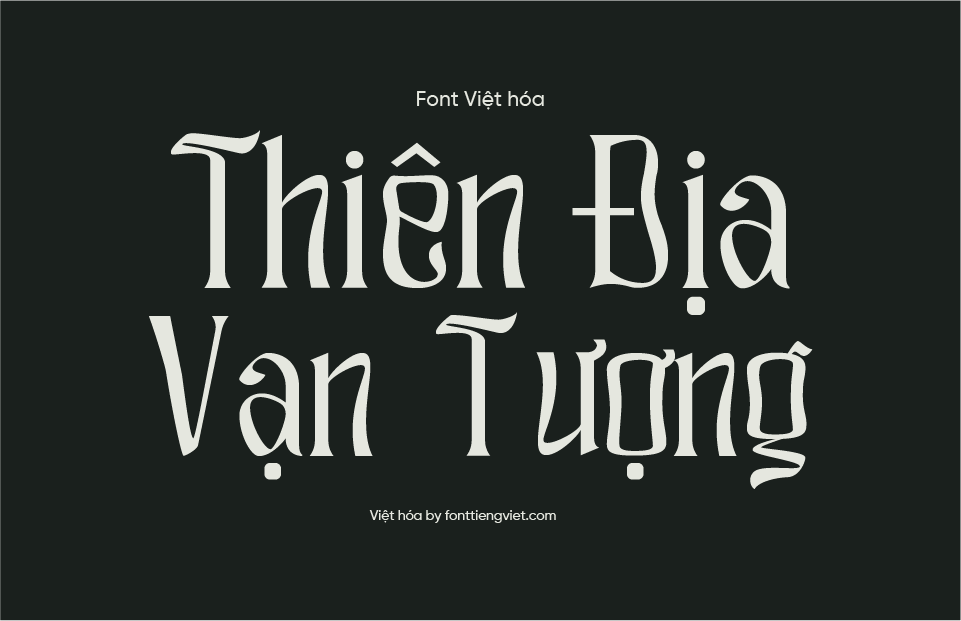
Font Việt hóa 1FTV Raghlick
Trong thế giới đồ họa hiện đại, việc lựa chọn một Font Miễn Phí chất lượng là yếu tố then chốt giúp tác phẩm trở nên ấn tượng. Font Việt hóa 1FTV Raghlick nổi lên như một lựa chọn hoàn hảo cho những ai đang tìm kiếm sự kết hợp giữa nét cổ điển và hơi thở hiện đại. Với bộ ký tự được chăm chút tỉ mỉ, phông chữ này giúp các bạn học sinh và giáo viên dễ dàng tạo ra những slide thuyết trình hay báo tường đẹp mắt mà không lo lỗi font tiếng Việt.
Khám phá đặc điểm nổi bật của Font Việt hóa 1FTV Raghlick
Bộ Font Việt hóa 1FTV Raghlick sở hữu những đường nét thanh mảnh nhưng vô cùng dứt khoát. Đây là kiểu chữ thuộc phong cách Serif cách tân, mang lại cảm giác sang trọng và chuyên nghiệp cho mọi khung hình. Đặc biệt, phiên bản 1FTV đã được tối ưu hóa hoàn toàn về dấu câu, giúp các nhà thiết kế tại Việt Nam sử dụng mượt mà trên mọi phần mềm từ Photoshop đến Microsoft Word.
Tính ứng dụng linh hoạt trong giáo dục và đời sống
Nhờ vẻ ngoài thanh lịch, phông chữ này thường được sử dụng để thiết kế bìa sách, tiêu đề bài giảng hoặc các ấn phẩm truyền thông học đường. Cấu trúc chữ dễ đọc giúp người xem tiếp nhận thông tin nhanh chóng, đồng thời vẫn giữ được tính thẩm mỹ cao. Bạn có thể kết hợp nó với các màu sắc trung tính để tạo nên sự trang nhã tuyệt đối.
Kết luận về bộ sưu tập font chữ chất lượng